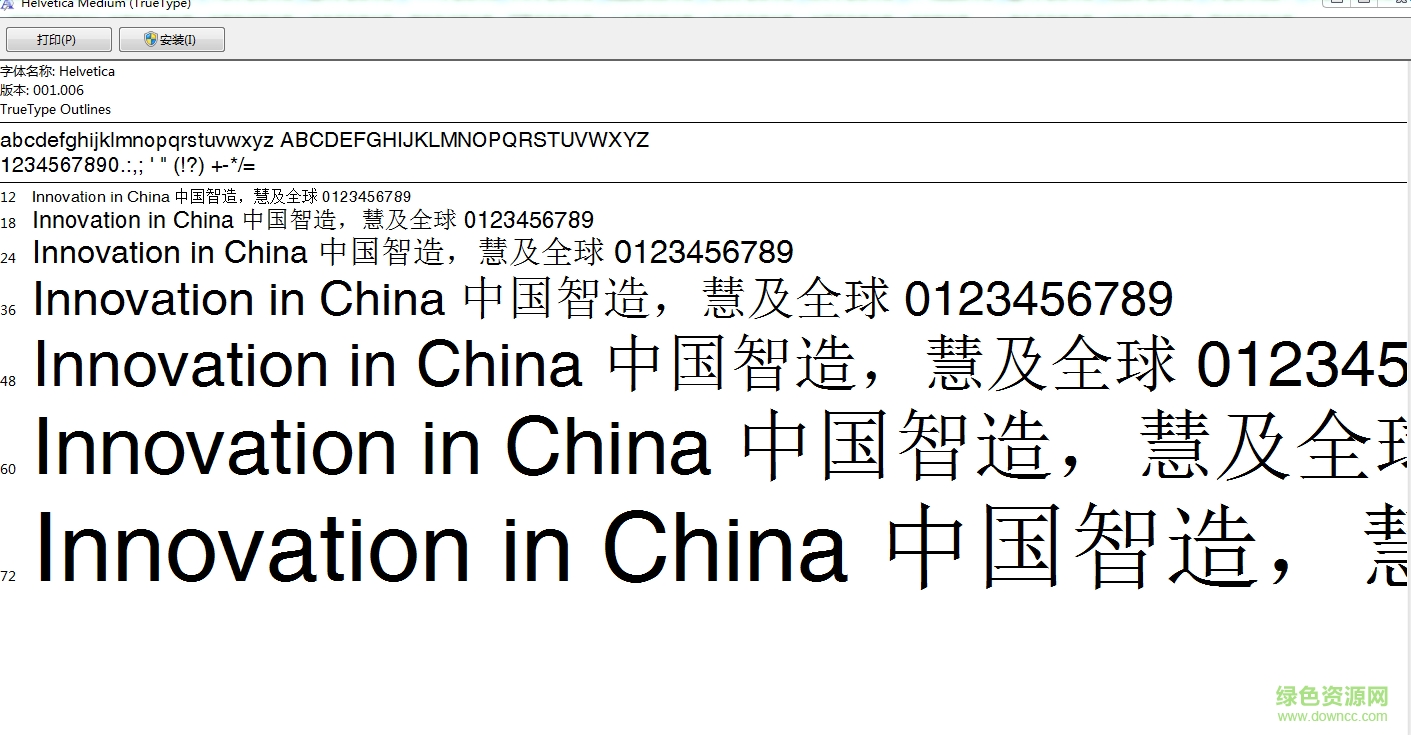
helvetica medium字體是一款無襯線英文字體,字體規(guī)范大氣,通用性高,常用于Logo設(shè)計、標(biāo)題、廣告等方面,喜歡的小伙伴快來綠色資源網(wǎng)下載吧!
helveticaneue medium字體是目前最常見的一款英文字體,字形大方得體,粗細均勻,結(jié)構(gòu)清晰,可用于包裝印刷、平面廣告、手稿設(shè)計、正文標(biāo)題等應(yīng)用,有喜歡的朋友可免費下載收藏。